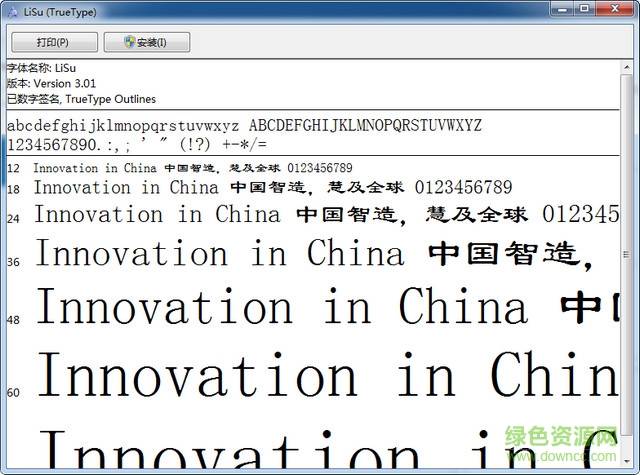
中易隸書字體是一款專門適用于正文設(shè)計方面的中文簡體漢字。該字體界面簡潔,使用方便。該字體端正大方得體,一筆一畫非常正規(guī),整體效果也非常出色,可以廣泛應(yīng)用于平面設(shè)計、廣告設(shè)計、報紙雜志、正文標題等領(lǐng)域,使用時請選擇“LiSu”即可,歡迎來綠色資源網(wǎng)下載。